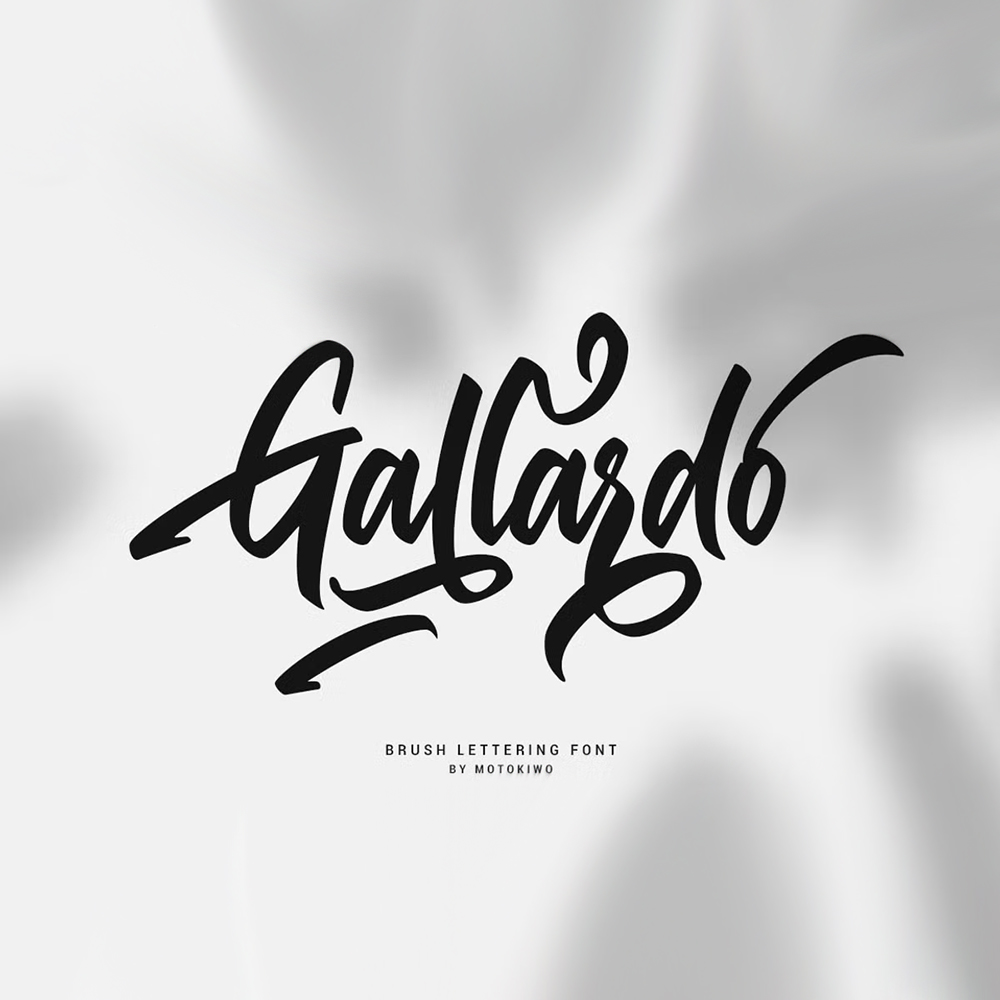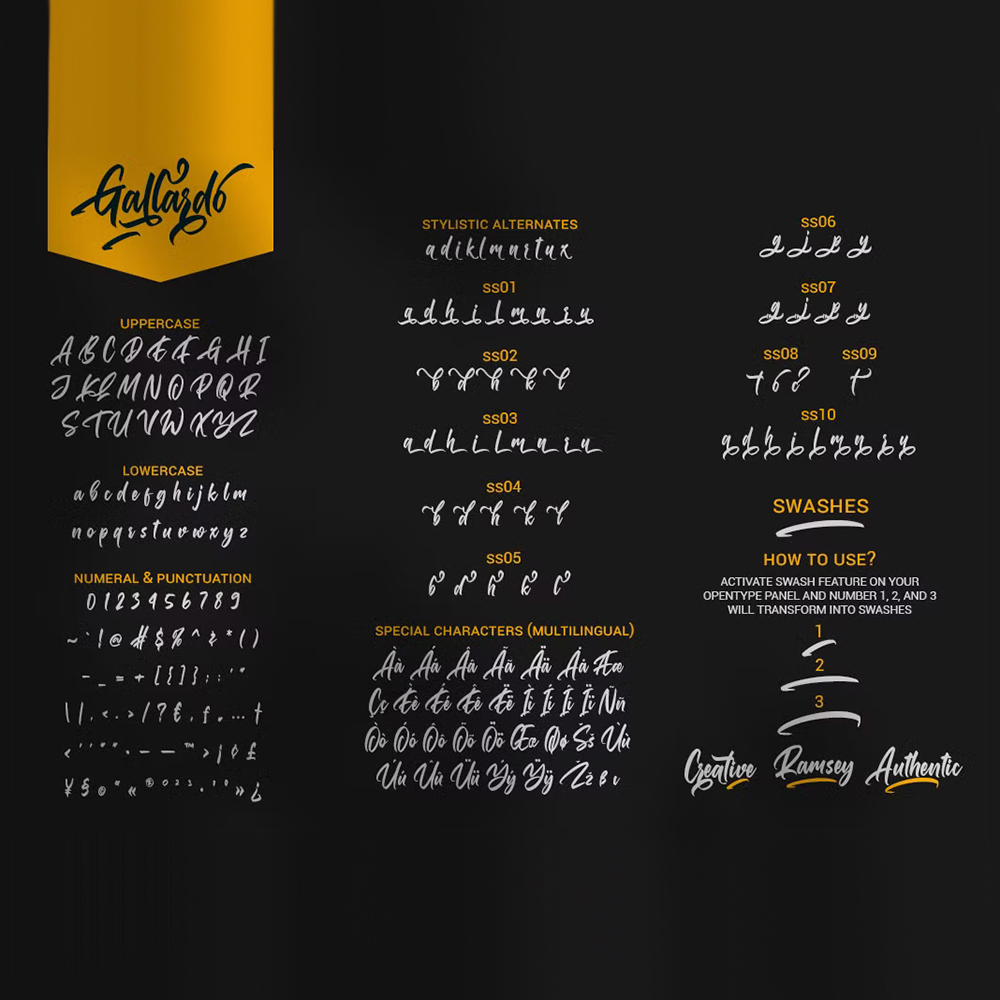
دانلود فونت انگلیسی Gallardo Font
فونت پرمیوم و انگلیسی Gallardo Font یک فونت حروفچینی سفارشی با تنوع زیادی است. این فونت تمیز، محکم و زیبا برای انواع پروژهها بسیار مفید است. این…
فونت پرمیوم و انگلیسی Gallardo Font یک فونت حروفچینی سفارشی با تنوع زیادی است. این فونت تمیز، محکم و زیبا برای انواع پروژهها بسیار مفید است. این فونت هم برای سبکهای شهری و هم سبکهای قدیمی عالی است. شما میتوانید به راحتی کلمات خود را با Gallardo شخصیسازی کنید زیرا این فونت با PUA رمزگذاری شده و از کاراکترهای ویژه برای استفاده چندزبانه پشتیبانی میکند.
مزایای استفاده از فونت لاتین Gallardo چیست؟